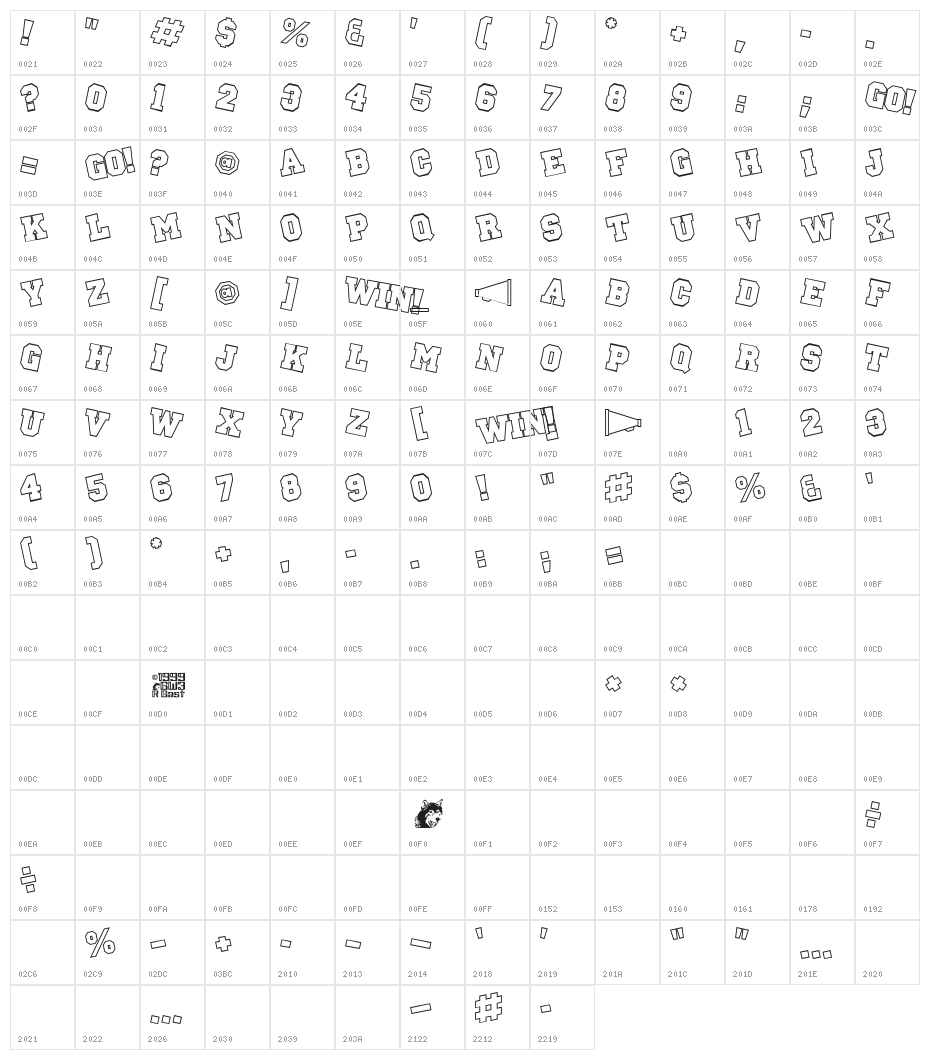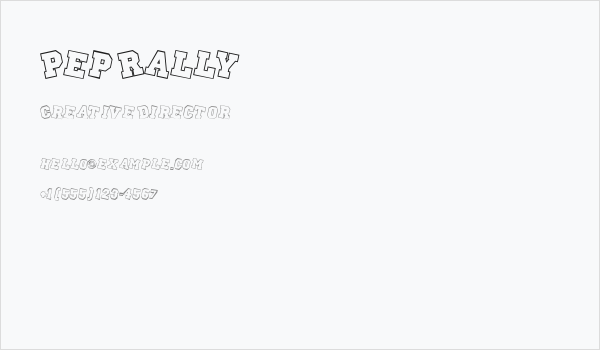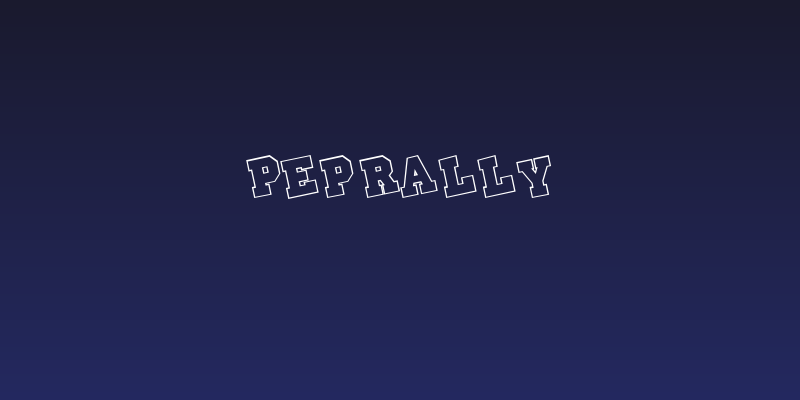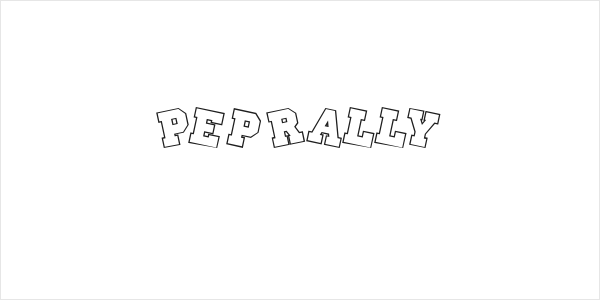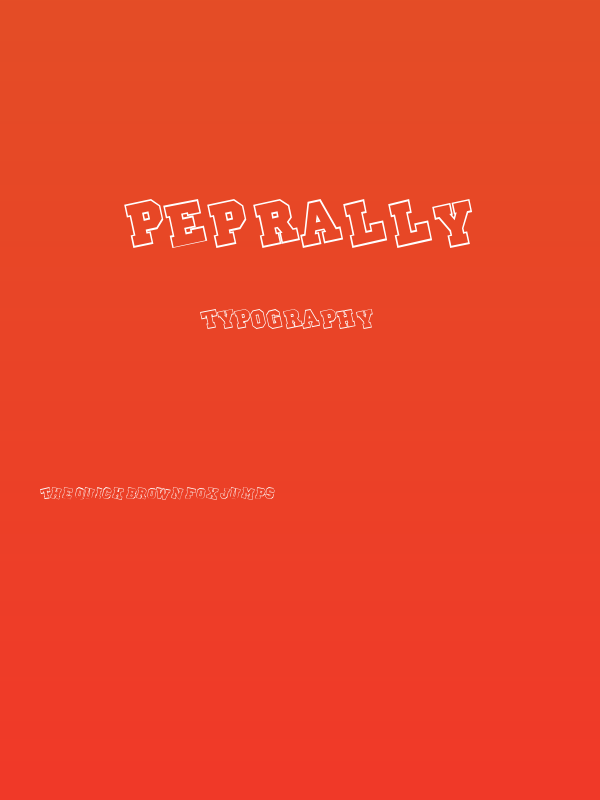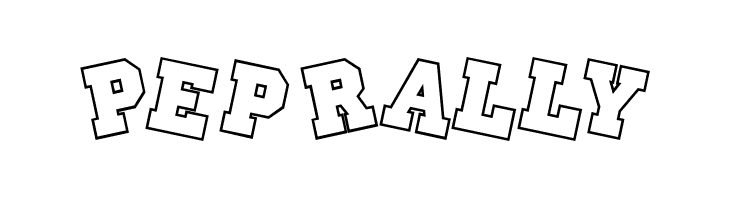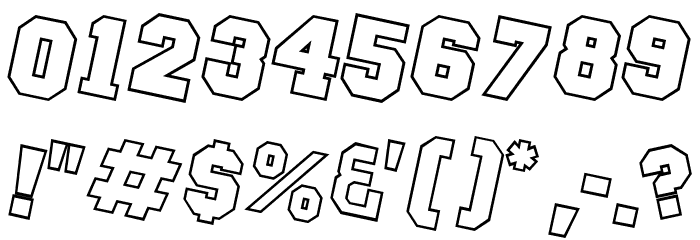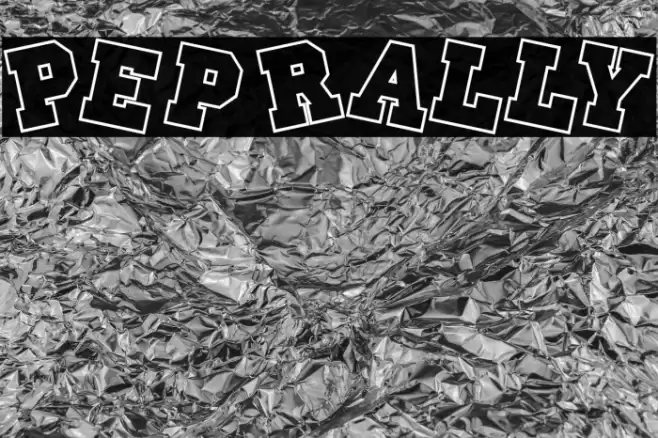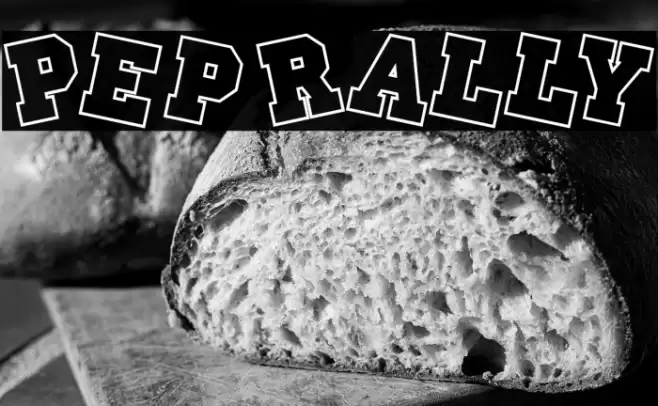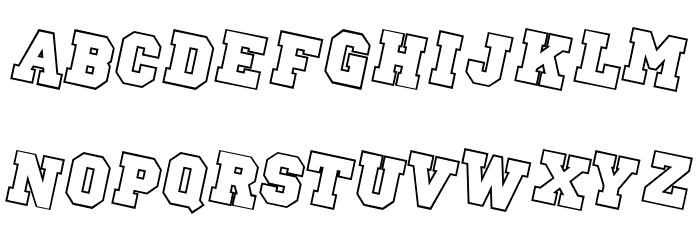
Pep Rally Font
✎ Old fashioned
| Style général | Energetic, Collegiate, Bold |
| Projets proposés | Ideal for sports team branding, event posters, school spirit merchandise, and dynamic headlines. |